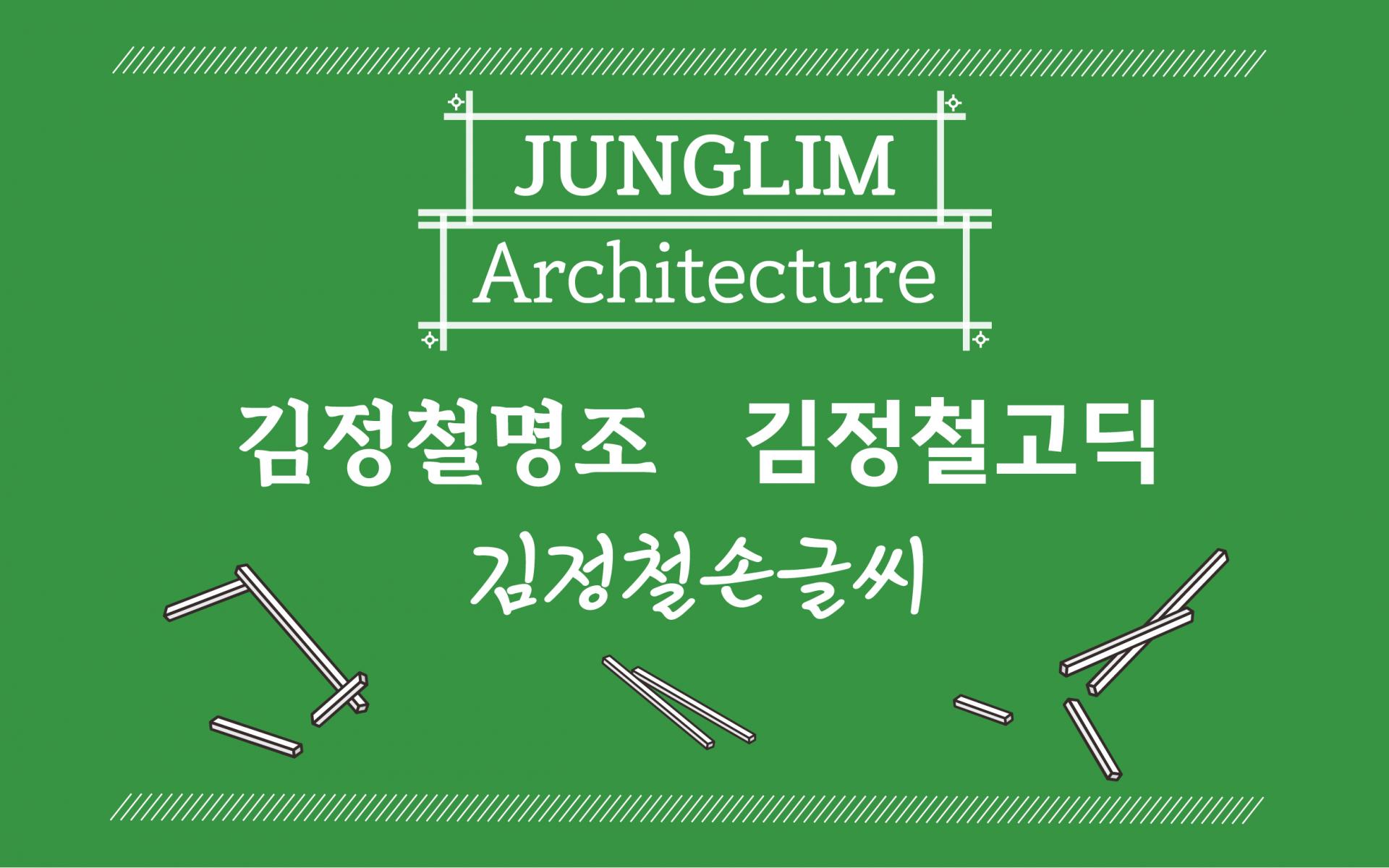
정림건축
정림건축 [김정철명조, 김정철고딕]
정림건축과 윤디자인그룹이 주관한 공모전의 당선작 원도를 바탕으로 개발된 서체. 일반적인 명조가 가진 뼈대에 맞춰 글자의 인상이 안정적으로 느껴질 수 있도록 디자인했다. 고딕은 명조와 같은 뼈대를 유지하되 고딕답게 재해석하였다.